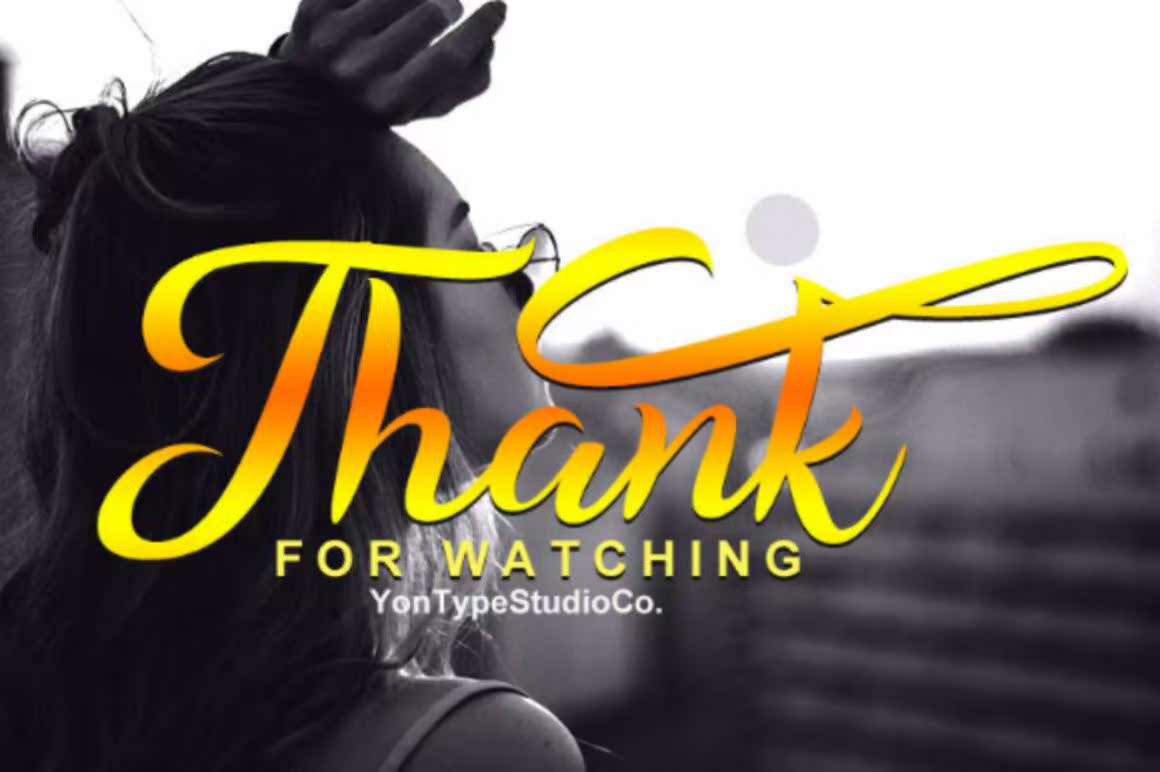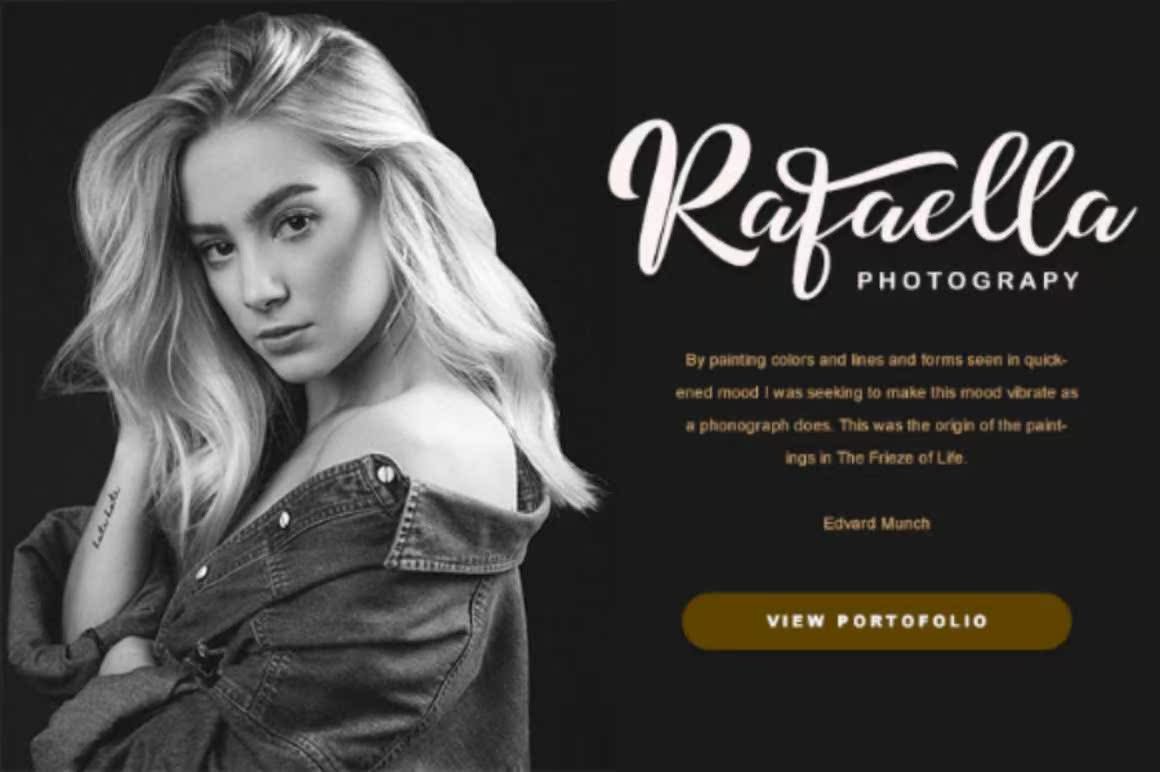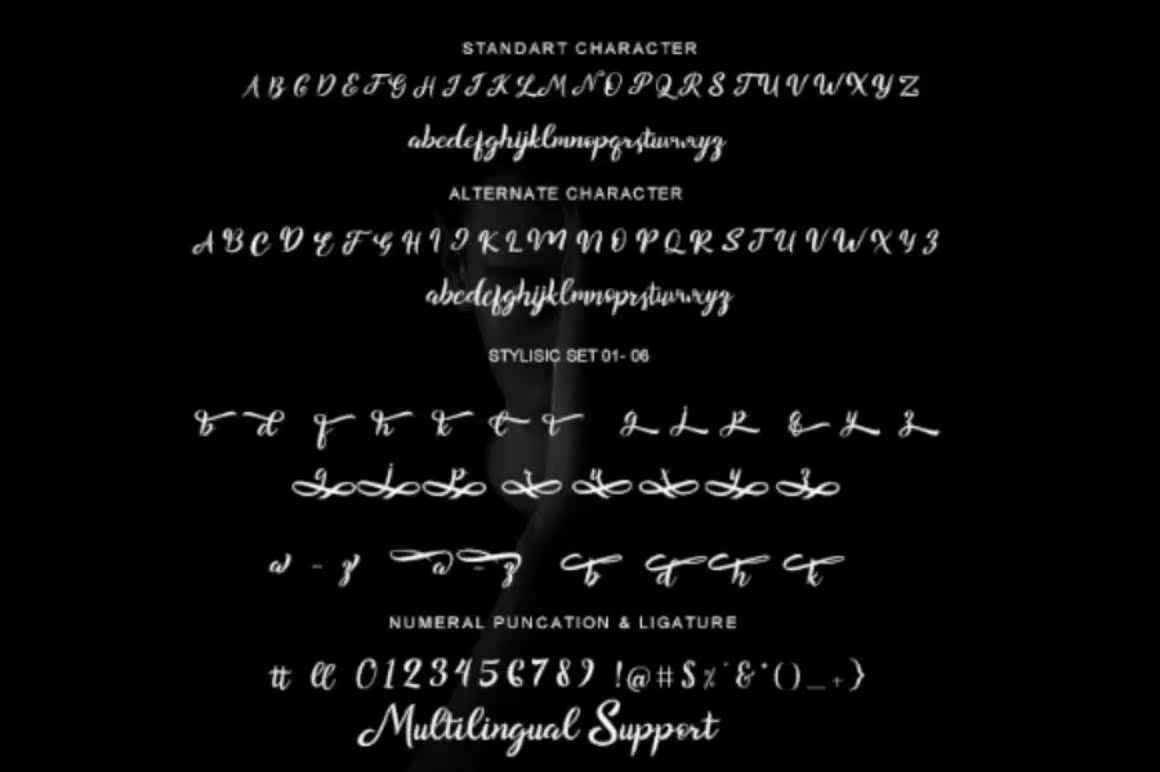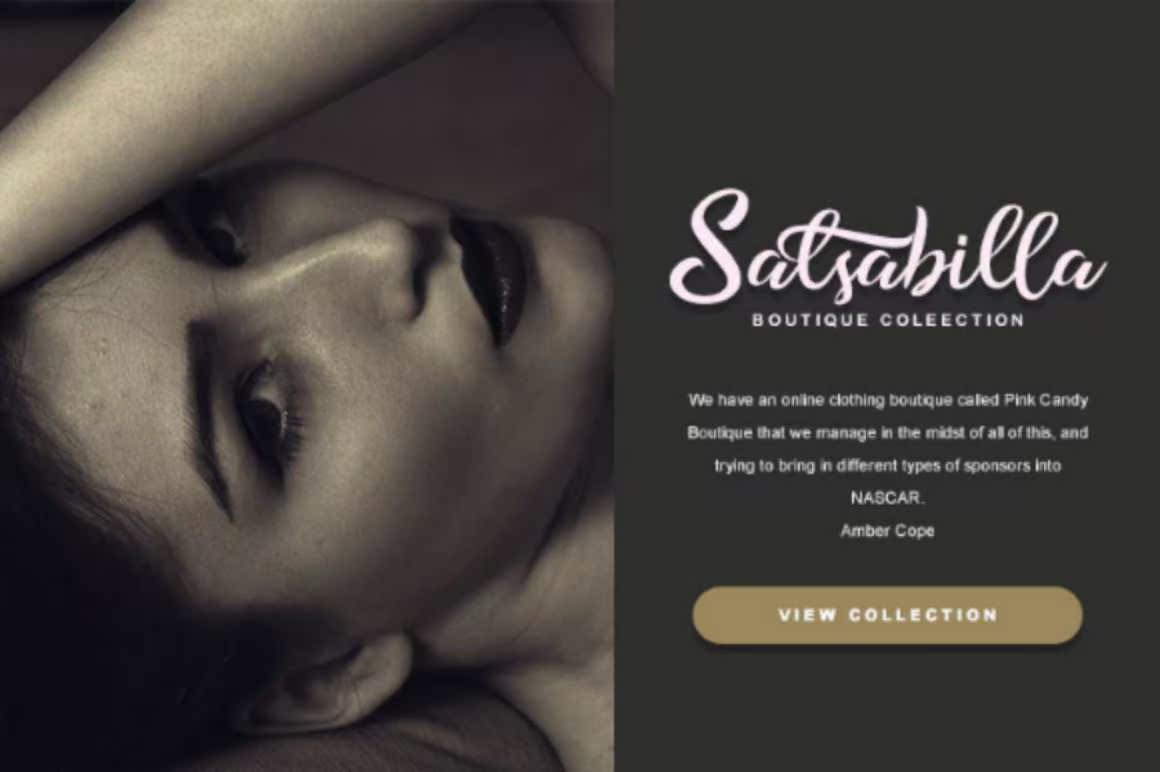
RinduTypefacefontwithaUniquestyle,ThisFontwillPerfectFormanyDifferentityProjectSex:报价、徽标、博客标题、海报、乐队、时尚、服装、信函、邀请函、文具等。RinduTypefacefontwithaUniquestyle,ThisFontwillPerfectFormanyDifferentityProjectSex:报价、徽标、博客标题、海报、乐队、时尚、服装、信函、邀请函、文具等…